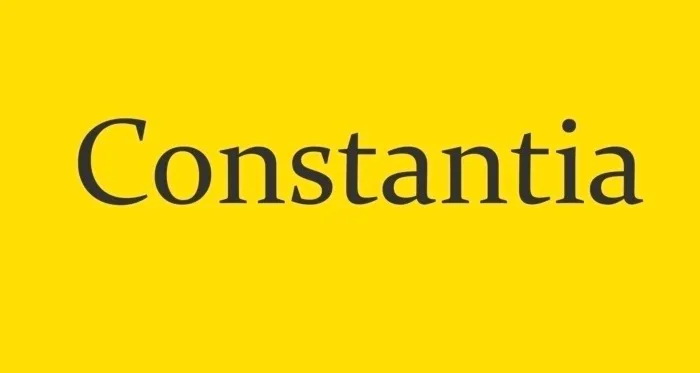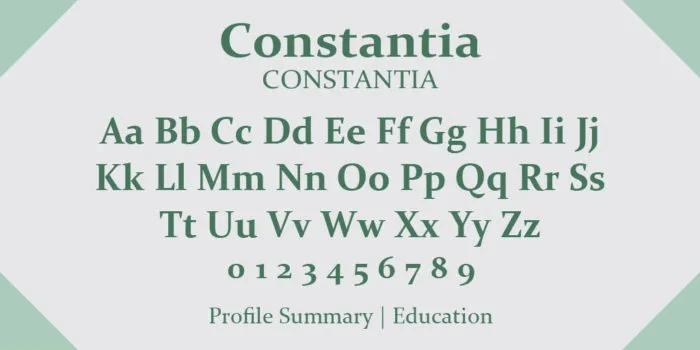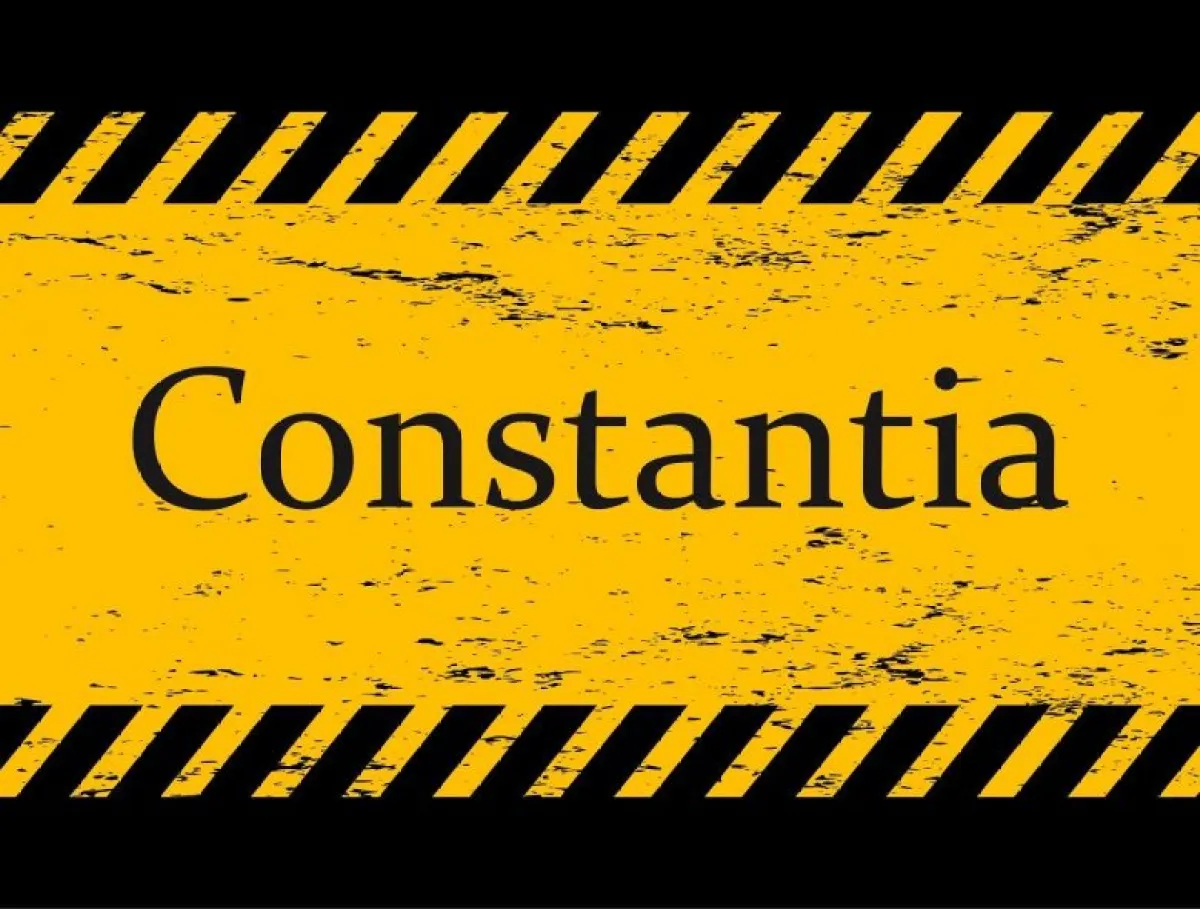
Constantia Font Việt hóa là bộ phông chữ có chân (Serif) chuyển tiếp kinh điển được sáng tạo bởi nhà thiết kế John Hudson cho tập đoàn Microsoft, nằm trong bộ sưu tập ClearType nổi tiếng toàn cầu. Với sự kết hợp hoàn hảo giữa cấu trúc chữ sách báo cổ điển và các góc chân chữ bo tròn nhẹ nhàng, Constantia toát lên vẻ đẹp đĩnh đạc, uy tín và sở hữu độ dễ đọc vượt trội trên cả màn hình kỹ thuật số lẫn bản in thực tế. Doozypack.vn cung cấp link tải Font Constantia Việt hóa chuẩn kỹ thuật, giúp bạn sở hữu phông chữ chuẩn mực này mà không lo gặp bất kỳ lỗi hiển thị dấu thanh nào khi thiết kế bao bì.
Đặc điểm thẩm mỹ độc đáo của Constantia Font
Constantia được nghiên cứu kỹ lưỡng để giải quyết bài toán đọc văn bản liên tục trong thời gian dài mà không gây mỏi mắt, mang lại cảm giác thoải mái và thư thái cho người tiếp nhận thông tin.
Phong cách Transitional Serif thanh lịch và chuẩn mực
Đặc trưng lớn nhất của Constantia Font Việt hóa là tỷ lệ chữ cân đối, trục chữ hơi nghiêng tự nhiên tạo nên một dòng chảy thị giác mượt mà dọc theo hàng chữ. Độ tương phản nét thanh đậm vừa phải giúp phông chữ giữ được độ sắc nét và hình khối rõ ràng, không bị quá mảnh mai như Didone hay quá nặng nề như Slab Serif. Khi đặt Constantia lên bao bì, thương hiệu của bạn sẽ ngay lập tức toát lên vẻ đáng tin cậy, chuẩn mực và mang tính chuyên gia cao.
Thiết kế chân chữ bo tròn mềm mại và tối ưu độ đọc hiểu
Khác với các dòng Serif sắc nhọn có thể gây cảm giác lạnh lùng, Constantia sở hữu phần chân chữ (serif) dạng tam giác được bo tròn nhẹ ở các góc. Chi tiết tinh xảo này giúp làm dịu đi sự cứng nhắc của văn bản hành chính, mang lại cảm giác ấm áp, gần gũi nhưng vẫn vô cùng trang trọng, cực kỳ ăn ý với các ấn phẩm sách báo, tài liệu giới thiệu năng lực doanh nghiệp và bao bì dược phẩm.
Ưu điểm nổi bật của bản Constantia Font Việt hóa
Khi ứng dụng các phông chữ chuẩn mực vào thị trường trong nước, sự chỉn chu về dấu câu là yếu tố quyết định đến tính chuyên nghiệp của bản thiết kế:
- Khắc phục triệt để lỗi dấu tiếng Việt: Phiên bản Việt hóa chuẩn đã được các chuyên gia trau chuốt thủ công từng dấu câu. Các dấu sắc, huyền, hỏi, ngã, nặng được vẽ với tỷ lệ cân đối, đặt ở vị trí thoáng đãng so với thân chữ, không gây cảm giác chắp vá hay làm biến dạng cấu trúc chữ.
| Biến thể Font | Đặc điểm thị giác | Ứng dụng đề xuất tại Doozypack.vn |
| Constantia Regular | Cân đối, thông thoáng, dễ đọc | Dùng cho nội dung hướng dẫn sử dụng, bảng thành phần (Body text). |
| Constantia Bold | Dày dặn, vững chãi, trang trọng | Dùng làm tiêu đề phụ, tên sản phẩm hoặc logo thương hiệu. |
| Constantia Italic | Nghiêng nhẹ, tinh tế, cổ điển | Dùng cho các trích dẫn ngắn, ghi chú hoặc lời cảm ơn trên vỏ hộp. |
03 Ứng dụng thực tế của font Constantia trong sản xuất bao bì tại Doozypack.vn
Sự trang trọng và minh bạch của Constantia mang lại hiệu ứng thị giác đắt giá trên các dòng sản phẩm bao bì thực tế do Doozypack.vn sản xuất:
- Bao bì Dược phẩm & Thực phẩm chức năng: Nét chữ chân tròn chuẩn mực gợi cảm giác an tâm tuyệt đối về chất lượng và độ an toàn của sản phẩm y tế.
- Hộp giấy Trà thảo mộc & Cà phê di sản: Tiêu đề thương hiệu in bằng font Constantia Bold kết hợp cùng chất liệu giấy Kraft nâu tạo nên phong cách mộc mạc nhưng đậm đà phong vị gia truyền.
- Hồ sơ năng lực & Hộp quà tặng doanh nghiệp: Nét chữ Serif đĩnh đạc giúp các ấn phẩm quà tặng doanh nhân toát lên vẻ lịch lãm, chuyên nghiệp và khẳng định vị thế uy tín.
Lưu ý kỹ thuật khi in ấn với phông chữ có chân Constantia
Việc sản xuất bao bì thực tế sử dụng các phông chữ có chân đòi hỏi sự am hiểu kỹ thuật chuyên sâu tại xưởng in Doozypack.vn:
- Kiểm soát kích thước chữ tối thiểu: Trên chất liệu giấy Ivory nhẵn mịn, Constantia vẫn hiển thị rất rõ ràng ở kích thước 5.5pt. Tuy nhiên, trên giấy Kraft thô nhám, bạn nên để size chữ tối thiểu từ 7pt trở lên để thớ giấy không làm mờ các chi tiết chân chữ.
- Hệ màu CMYK chuẩn cho văn bản nhỏ: Luôn chuyển thiết kế về hệ màu CMYK và đặt màu đen cho văn bản nhỏ ở thông số K=100 đơn sắc để tránh hiện tượng nhòe màu do lé bản kẽm khi in chồng nhiều màu.